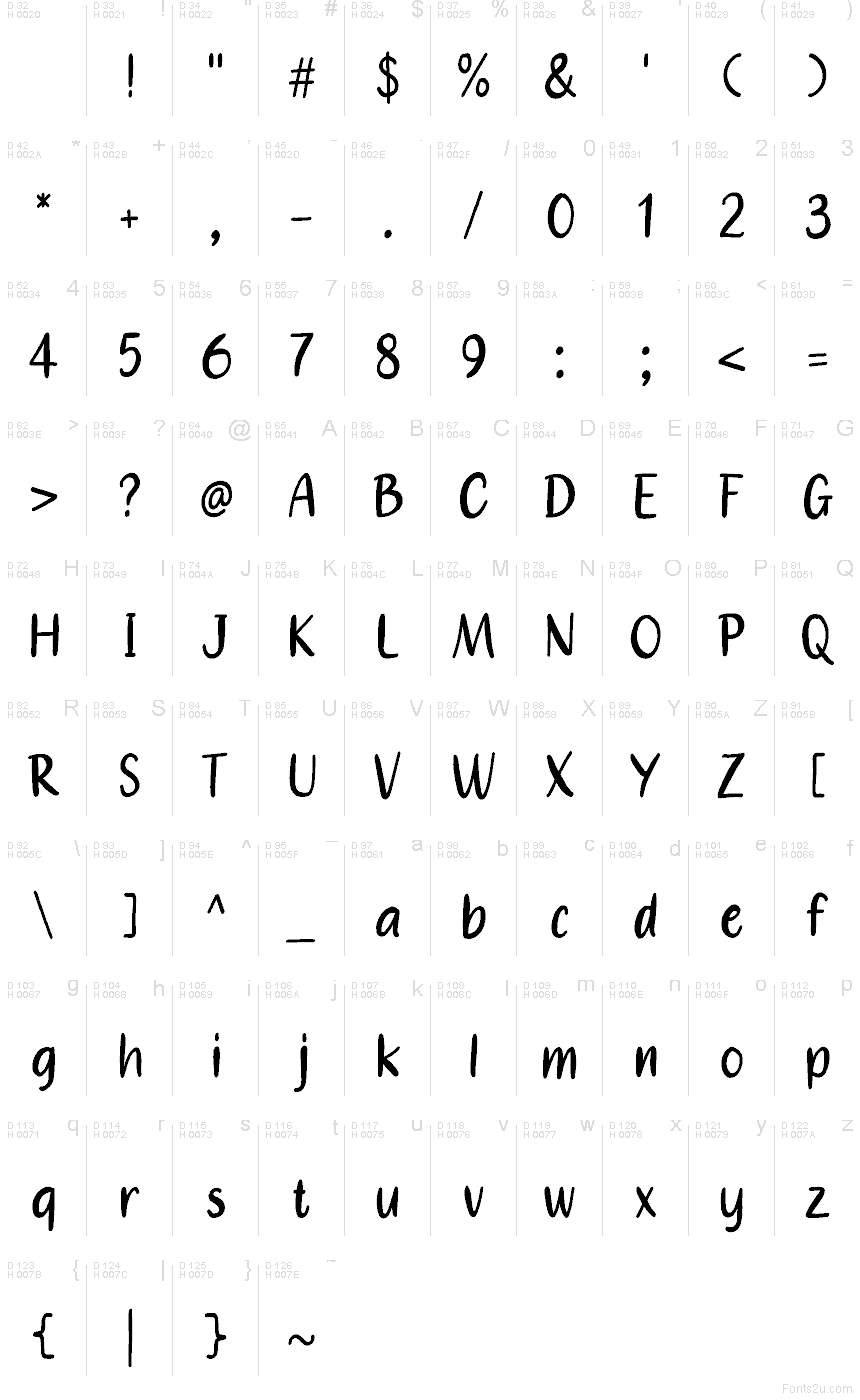
Until Create
Until Create від Hello Good Studio - це безкоштовний рукописний шрифт із легкими округлими штрихами та природним, невимушеним ритмом. Літери зберігають приємну нерівномірність завдяки простим вигинам, вузьким з'єднанням і м'якому, неформальному потоку, що створює враження справжнього рукописного письма, а не механічної конструкції.
Until Create чудово підходить для логотипів, графіки з цитатами, запрошень, пакування, дописів у соціальних мережах і коротких текстів, де важливо додати особистого стилю. Його рукописна структура надає проектам розслабленого, людяного тону без надмірної декоративності, тому він ідеально пасує для робіт, де потрібен швидкий акцент у стилі підпису.